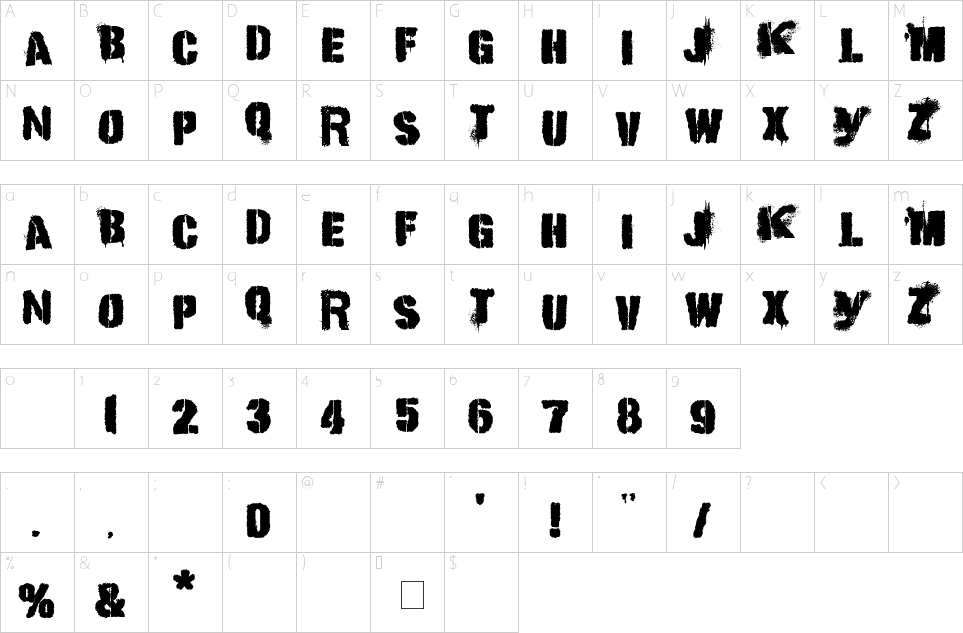
Descobrir uma nova fonte para projetos de design pode ser uma aventura, e a fonte Punk Kid é um caso perfeito para quem procura algo descompromissado e único. Este é um estilo de fonte que não se conforma com as regras normais, parecendo uma mistura perfeita entre o punk e a infantilidade, criando um efeito desafiador e divertido. Esta fonte foi criada por Christopher Hansen, um designer desconhecido de uma fonte que se destacou por sua originalidade e habilidade em capturar os sentimentos jovens e alternativos. Com um design agressivo e atraente, Punk Kid não apenas traz uma identidade única para suas criações, mas também uma sensação vibrante e irreverente que certamente marcará seu design. O Punk Kid é uma opção excelente para quem procura uma fonte única e divertida para projetos pessoais ou de design. Foi baixada mais de 16.985 vezes, o que mostra que muitos designers concordam com a qualidade desta fonte. Sem dúvida, a fonte Punk Kid é uma ótima adição a qualquer coleção de fontes.